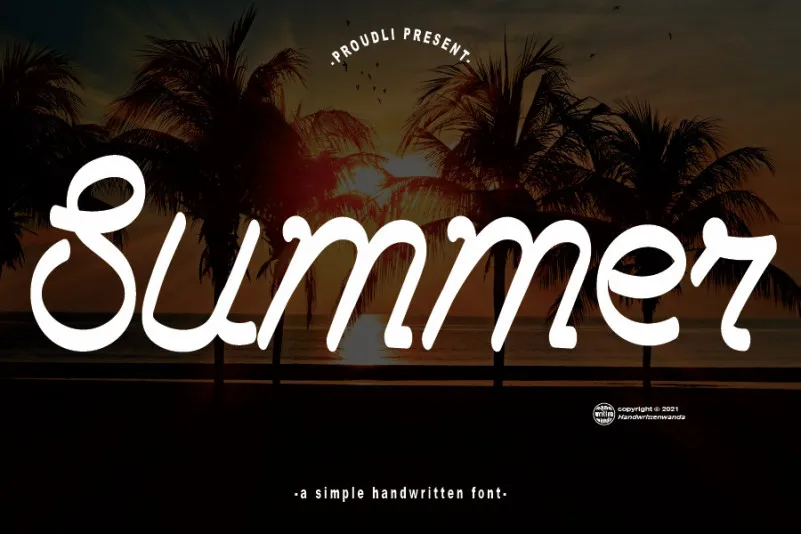
Summer Font – Download Grátis
Aqui está uma descrição para a página de download da fonte ‘Summer Font’, seguindo as instruções fornecidas: ‘Este é um belo e flexível tipo de mão escrita, perfeito tanto para projetos básicos quanto para ideias mais elaboradas. A Summer Font tem um toque quente e peculiar que se tornará uma paleta de cores atraente para qualquer projeto. Com esta fonte encantadora, você pode explorar inúmeras combinações únicas. Tem uma sensação geral de diversão e criatividade, certificando-se de que suas obras de arte serão notáveis. Prepare-se para se divertir enquanto experimenta as diversas variações desta fonte atraente.’
Designer: handwrittenwanda